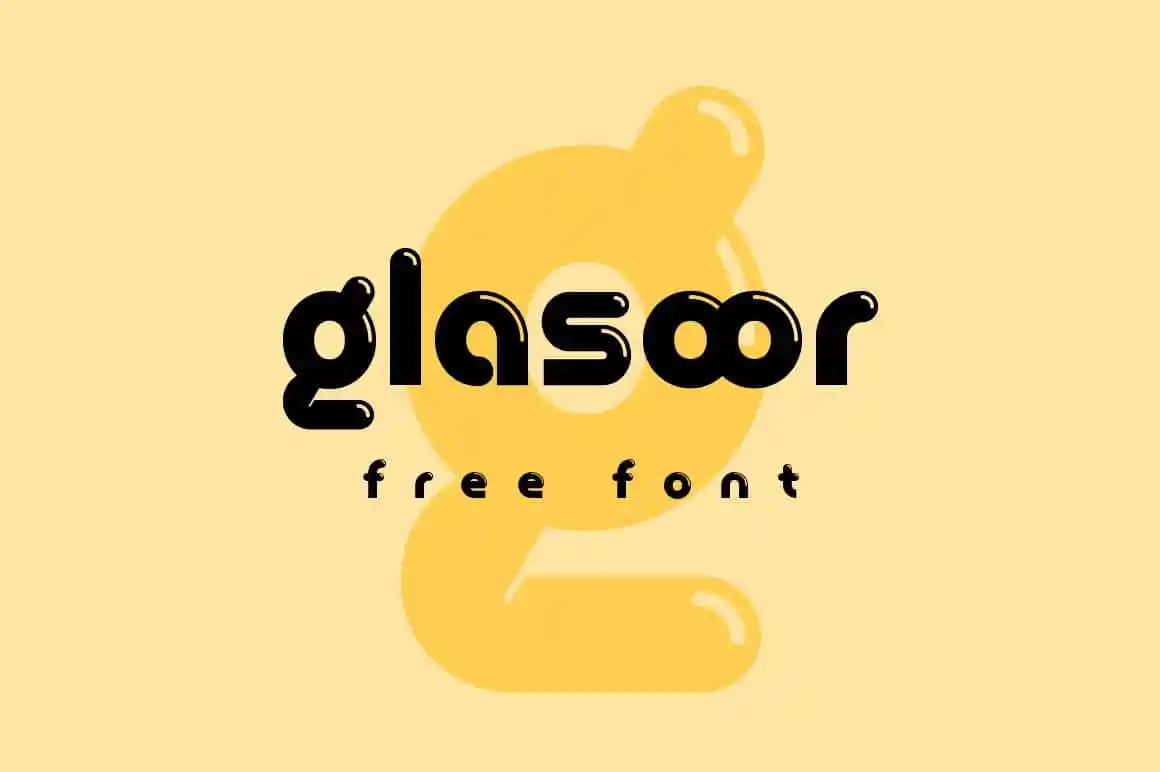
Glasoor Font – Download Grátis
Aqui está uma versão para português do Brasil de 2 parágrafos curtos, descrevendo a fonte ‘Glasoor Font’ de forma envolvente e natural: A fonte Glasoor é um moderno e elegante estilo que traz a graça da estética minimalista à sua próxima criação. Desenvolvida pelo designer Hamilton, esta fonte destaca-se por sua capacidade única de se adaptar tanto aos textos quanto às ilustrações. Seja para adicionar um toque refinado em design gráfico ou criar uma identidade visual intrigante, Glasoor está aqui para fornecer a perfeição dos detalhes que o seu trabalho merece. Acesse agora e desfrute deste estilo singular.